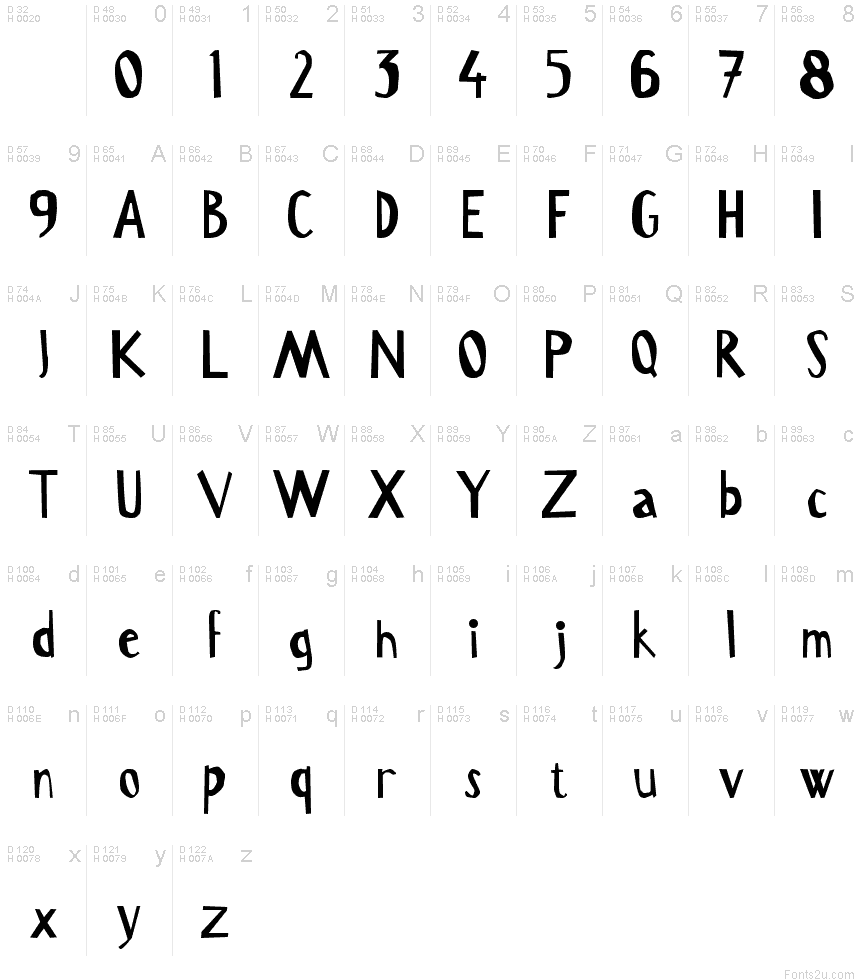
Serru من تصميم Jenny Barck هو خط عرض (display) مجاني ومشوّه، يتميز بإيقاع سلكي ومتذبذب قليلاً يجعله يبدو مرسوماً باليد أكثر من كونه مصمماً رقمياً. تمزج الحروف بين الأشكال الطويلة والنحيفة مع انحناءات مفاجئة ومنحنيات معقوفة، مما يمنح الخط حركة مرنة ومضطربة قليلاً، تبدو مرحة أكثر من كونها فوضوية.
يعمل هذا الخط بشكل رائع في عناوين الملصقات، وأغلفة المجلات المستقلة، ومنشورات الموسيقى المستقلة، ورسومات الفعاليات الفنية، والتغليف غير التقليدي، حيث يمكن لهذه الصورة الظلية الممتدة والمتمايلة أن تحمل جملة قصيرة بمفردها. كونه خطاً مجانياً، يناسب Serru أيضاً بطاقات العناوين والاقتباسات الكبيرة، خاصة عندما تبحث عن حروف تبدو غريبة ونحيفة ومسرحية بعض الشيء دون أن تتحول إلى زخرفة.